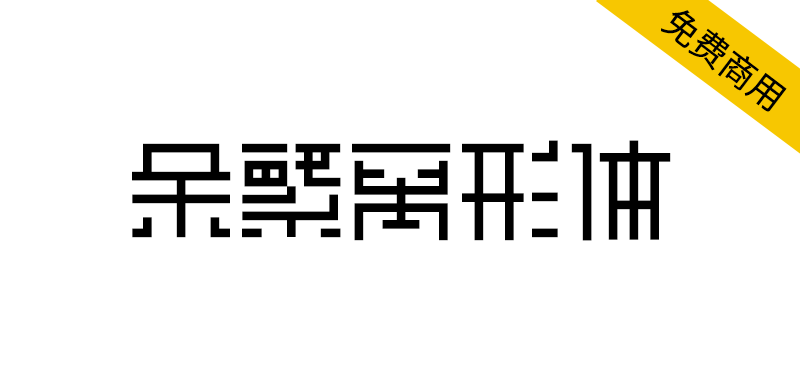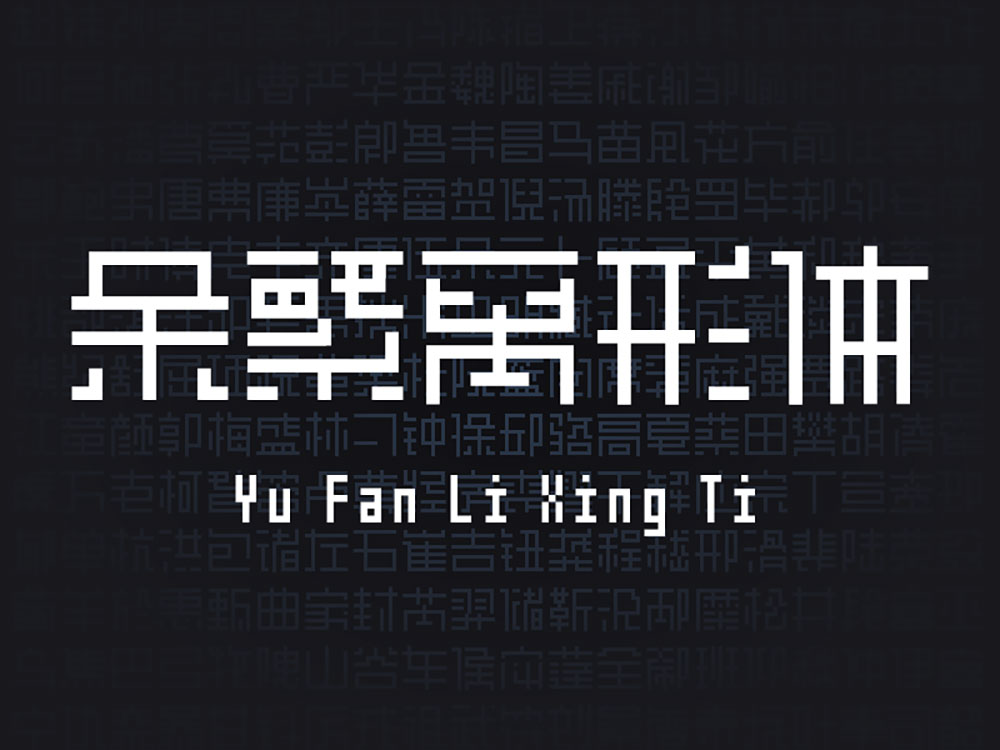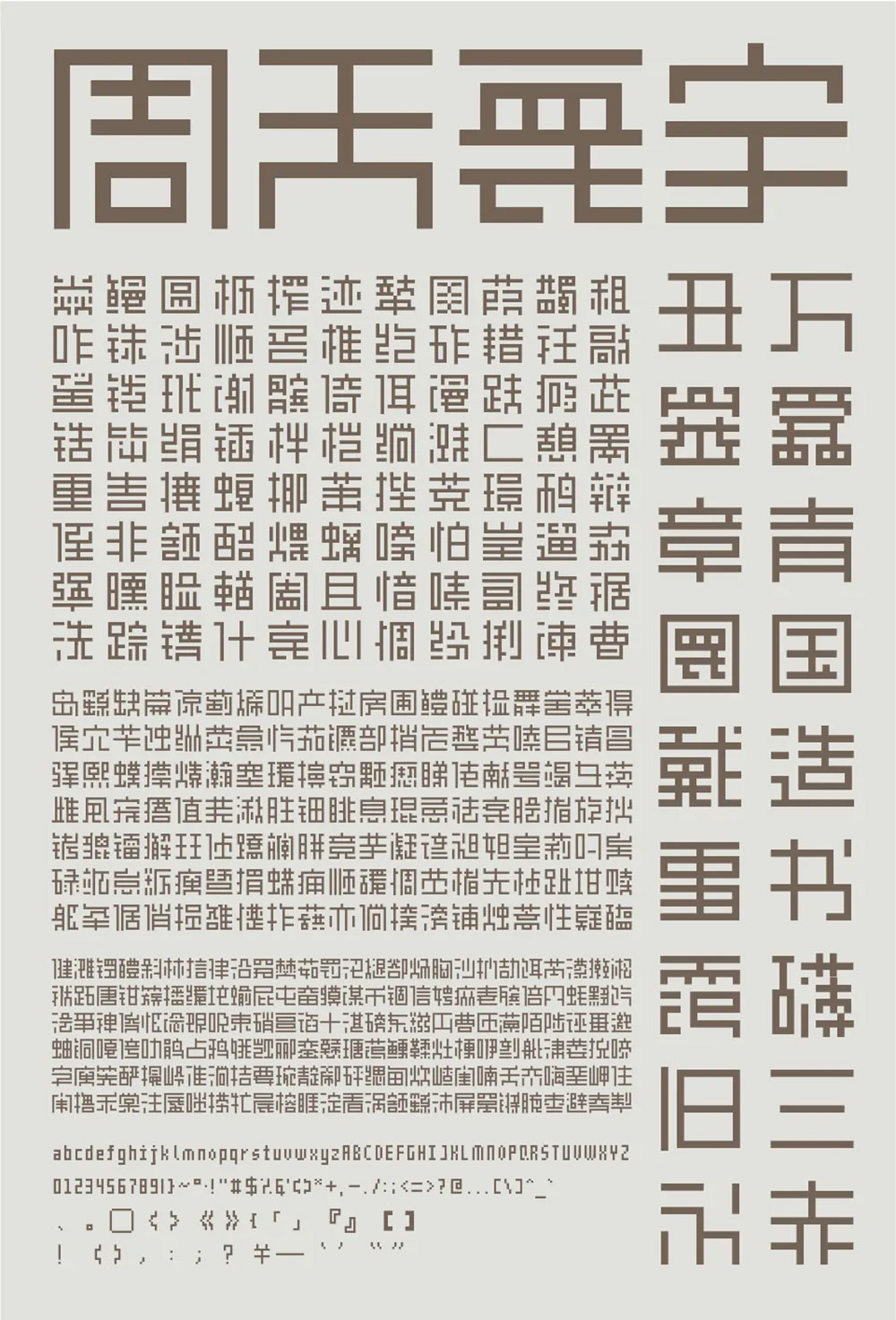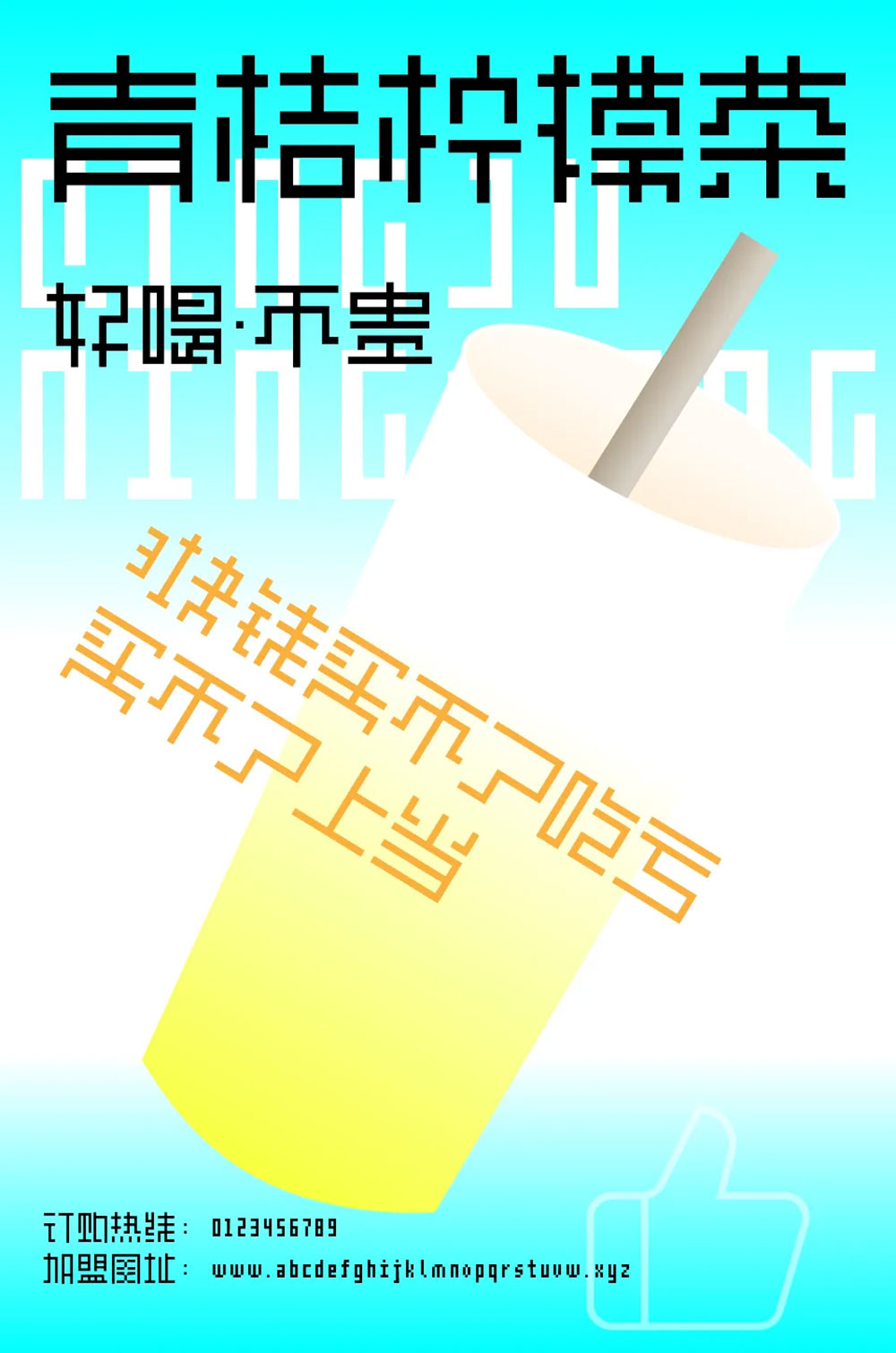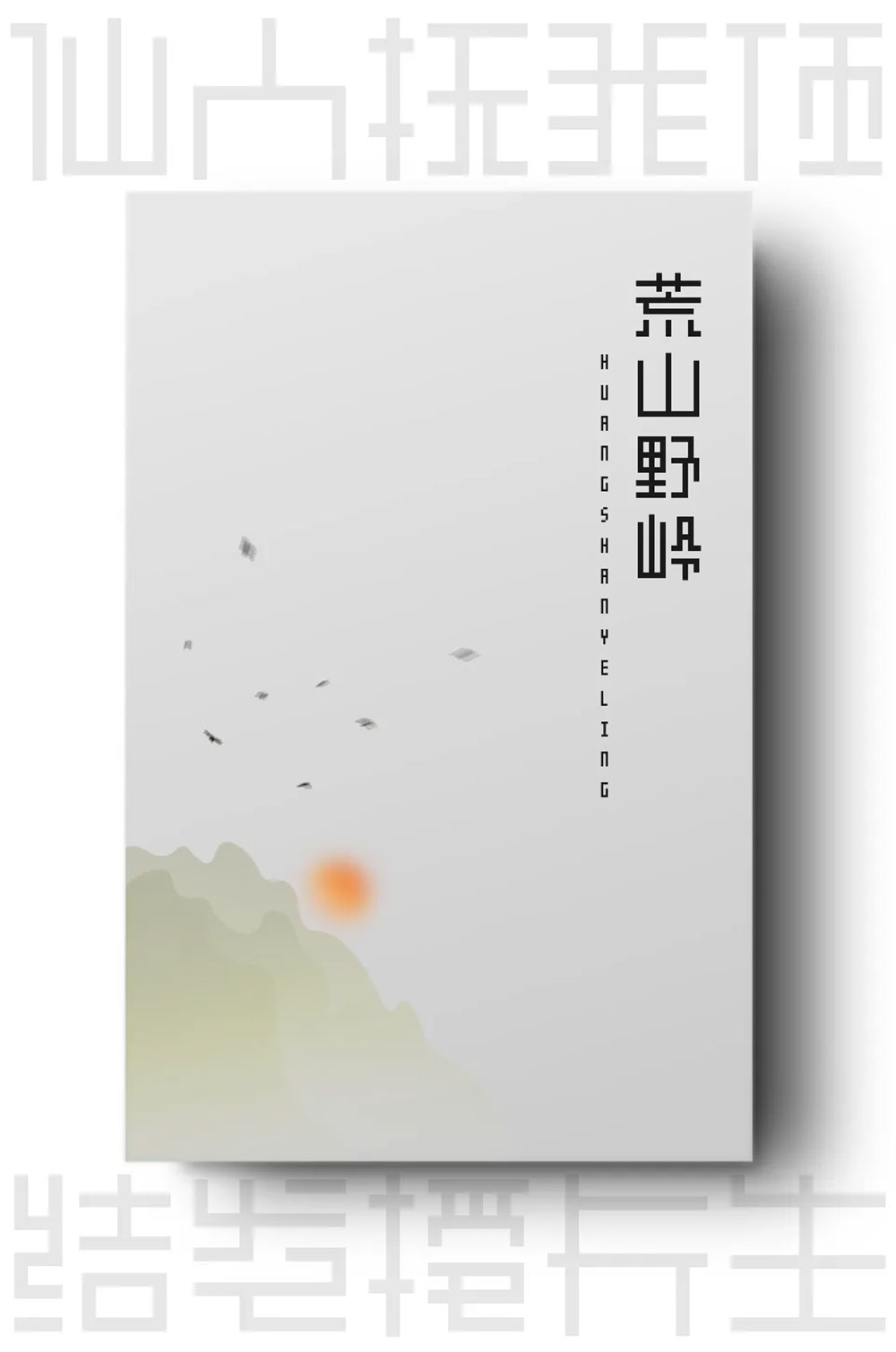
余繁离形体是一款类像素体的开源免费商用字体。与像素体相同之处为:1)以笔画宽度为基准,有最大尺寸限制(11X11);2)笔画由点与横竖线构成。
由于存在尺寸限制,对于复杂的字型必然是要简化的。其简化策略为:优先在保持部件外围结构的情况下简化部件的笔画(例:目→日→口),其次才会考虑改变复合部件的结构(例:吕→日)。简化字型会导致字型辨识度降低(也可以说是错误字型),若是着实不能接受,请谨慎考虑是否使用。